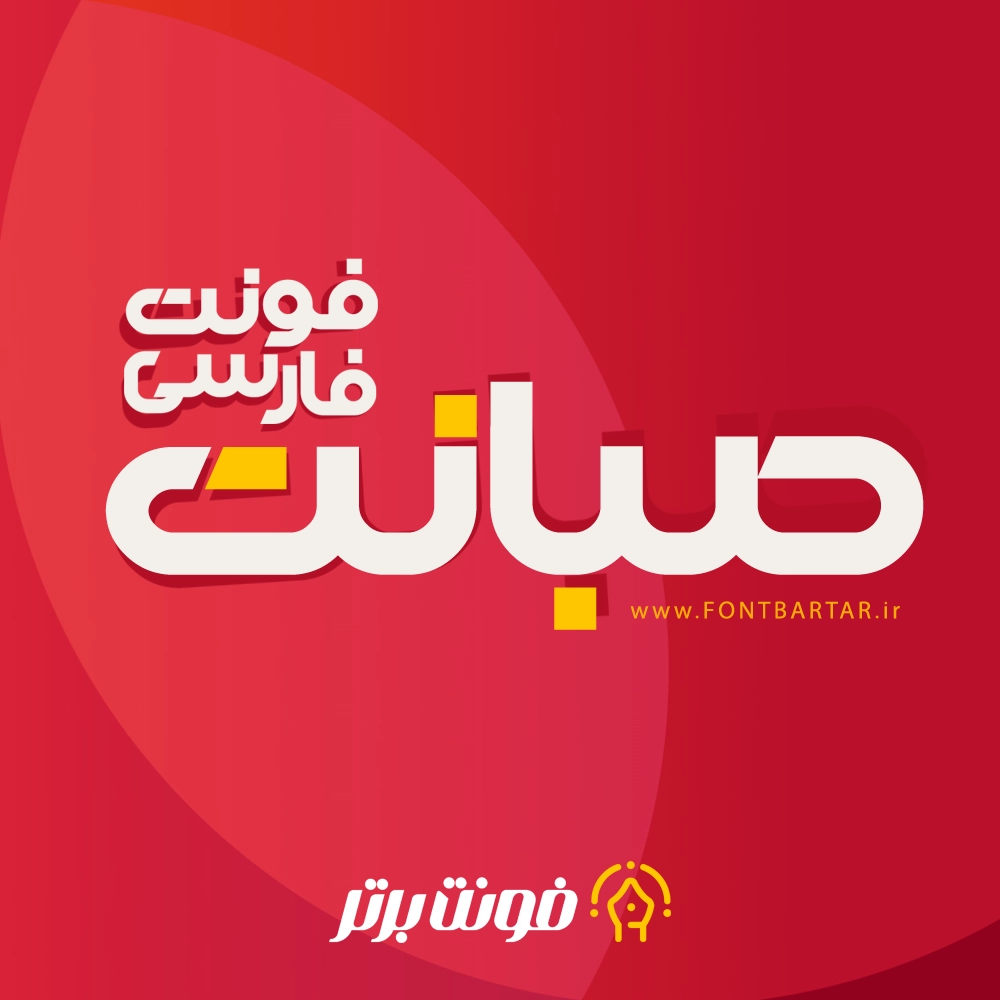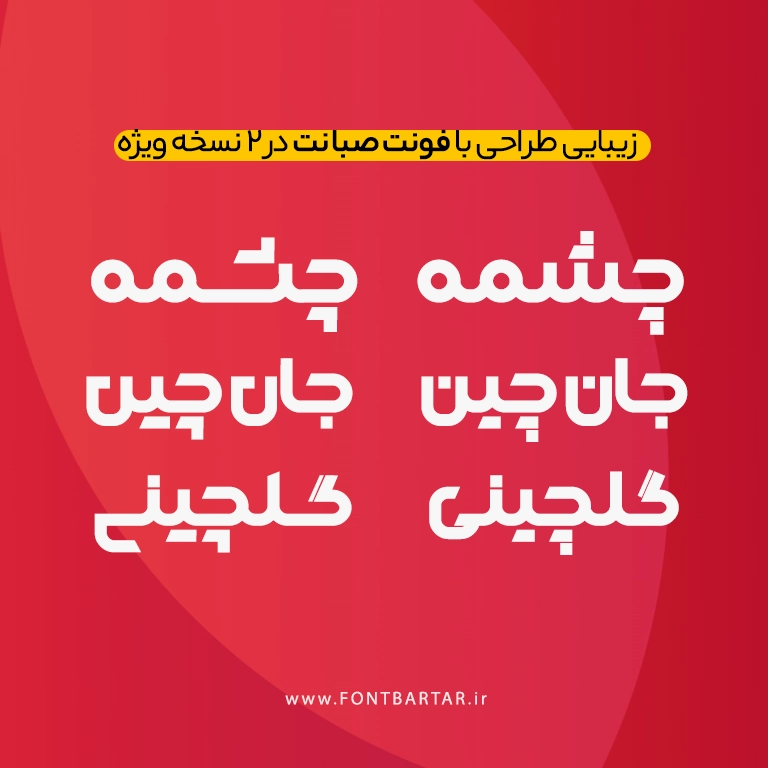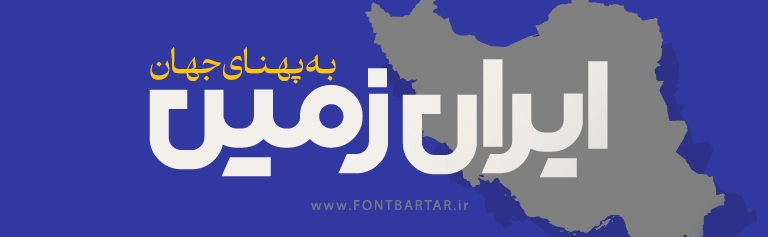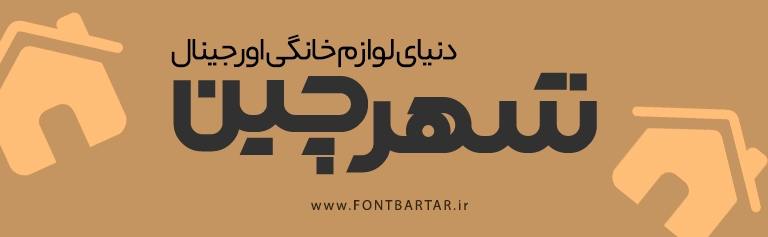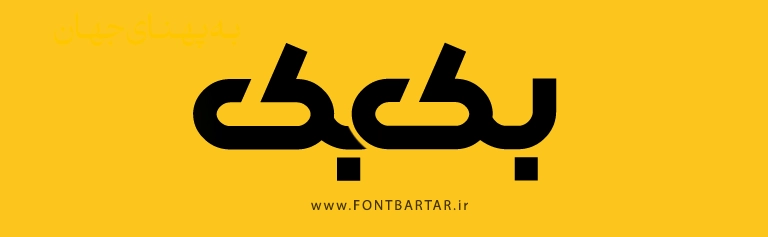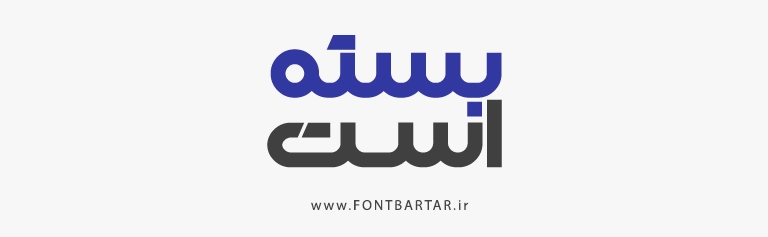
فونت جدید صبانت
فونت فارسی صبانت
Sabanet Font
فونت فارسی صبانت
دانلود فونت صبانت – فونت فارسی مدرن برای طراحی حرفه‌ای
فونت فارسی صبانت یکی از جدیدترین فونت‌های مدرن و مینیمال است که با طراحی ساده اما قدرتمند خود، انتخابی عالی برای طراحان گرافیک و تولیدکنندگان محتوا به شمار می‌رود. دانلود فونت فارسی با خطوط هندسی و یک‌دست خود حس مدرنیته و خوانایی بالا را به نوشته‌های شما می‌بخشد.
اگر به دنبال فونتی هستید که هم برای لوگو مناسب باشد و هم در طراحی پوستر، کارت ویزیت یا محتوای دیجیتال بدرخشد، فونت صبانت دقیقاً همان چیزی است که نیاز دارید.
ویژگی‌های فونت صبانت
• طراحی مدرن و مینیمال با ظاهری یک‌دست
• پشتیبانی کامل از حروف فارسی و علائم نگارشی
• مناسب برای لوگوتایپ، پوستر، رابط کاربری وب‌سایت و اپلیکیشن‌ها
• خوانایی بالا حتی در متن‌های طولانی
SabaNet Font new
چرا فونت صبانت انتخاب مناسبی است؟
دانلود فونت با ظاهری مدرن و طراحی دقیق، به نوشته‌های شما هویت خاصی می‌بخشد. این فونت مناسب برندهایی است که می‌خواهند سادگی و قدرت را همزمان منتقل کنند. همچنین برای استفاده در تبلیغات دیجیتال، استوری‌های اینستاگرام و طراحی‌های چاپی یک انتخاب ایده‌آل است.
کاربردهای فونت صبانت
• طراحی لوگو و برندینگ
• ساخت پوسترهای تبلیغاتی و فرهنگی
• طراحی رابط کاربری وب‌سایت‌ها و اپلیکیشن‌ها
• تایپوگرافی مدرن و خلاقانه
• استفاده در کارت ویزیت، بروشور و کاتالوگ‌ها
• تولید محتوای دیجیتال برای شبکه‌های اجتماعی